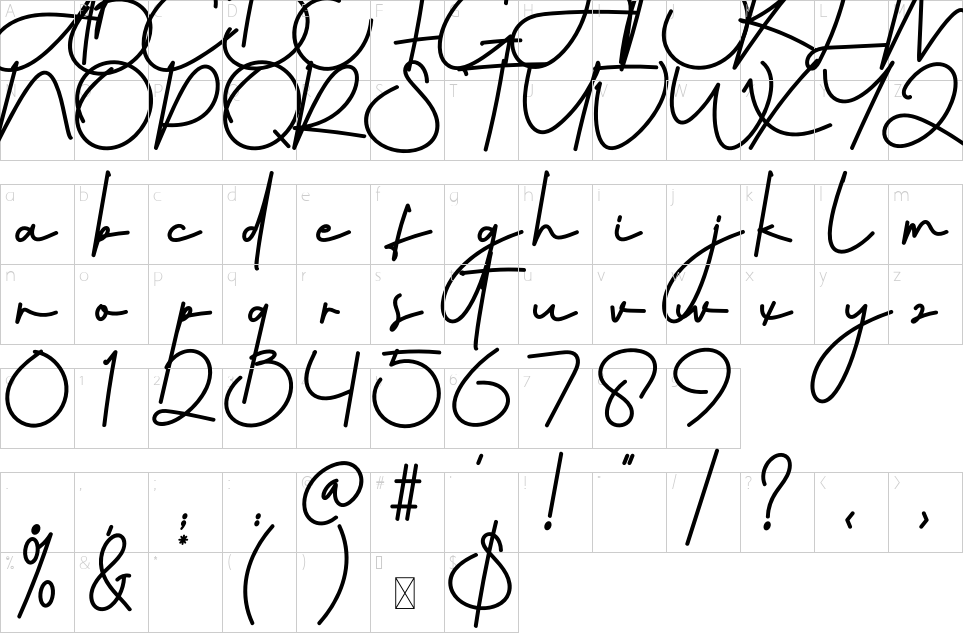
Descubra Angelina, uma fonte de graça projetada para agregar elegância e simplicidade a qualquer projeto. Esta font foi desenhada por scratchones, e já foi baixada 259 vezes. Com suas linhas finas e harmoniosas, Angelina é perfeita para criações que exigem um toque suave e agradável aos olhos. Seja para criar design de gráficos, criar materiais para a web ou apenas adicionar um toque de elegância a suas escritas, Angelina é uma escolha inteligente para qualquer designer gráfico. O design limpo e minimalista da font permite que ela se adapte a uma variedade de estilos e usos, tornando-a uma fonte versátil e inovadora. Descubra por si mesmo o quanto Angelina pode adicionar à sua próxima criação visual.